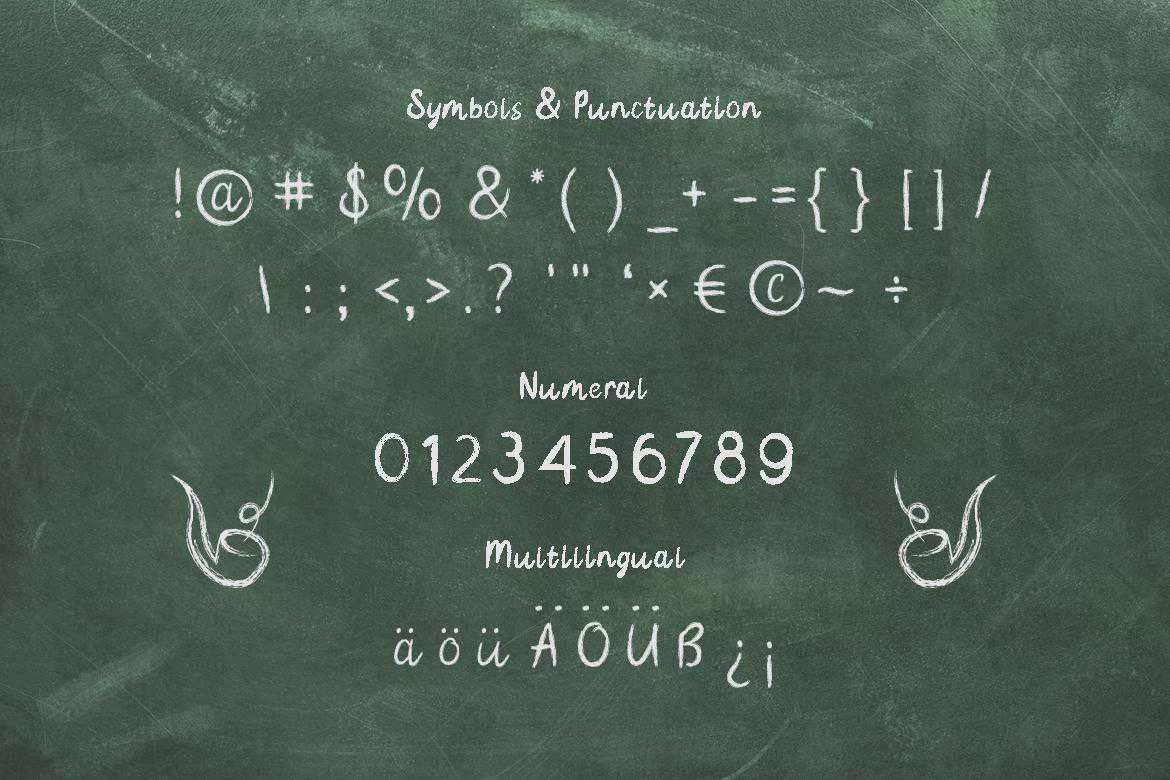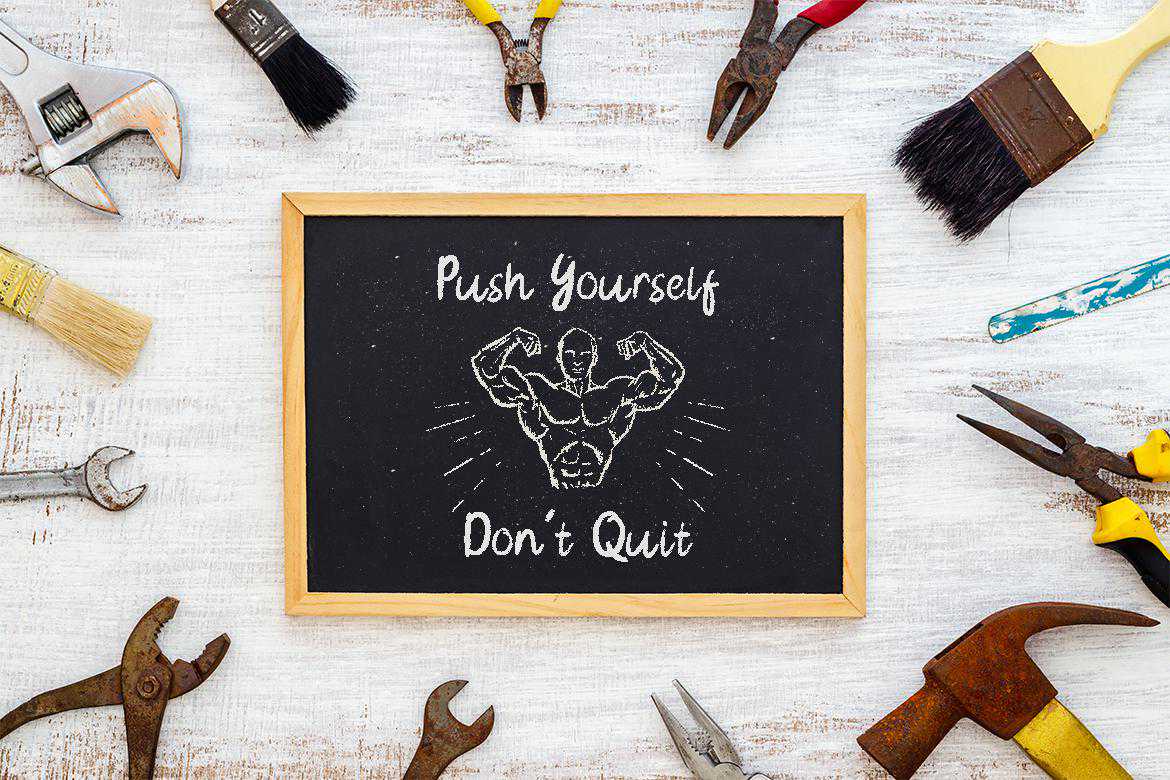
ScareMate是手工制作的DechalkFont。这款大胆、有趣、时尚的Font可用于各种不同的内容需求和项目。可制作GorgeousPartyVitations、打印报价、standoutpackaging或Beautiful衬衫!您甚至可以使用它来创建令人惊讶的标题、徽标、菜单和社交媒体。完整版本下载此处:ScaredMate是手工制作的。此粗体、有趣和时尚的字体可用于各种不同的内容需求和项目。创建GorgeousPartyVitations、打印的报价、standoutpackaging或美丽的衬衫!您甚至可以使用它来创建令人惊讶的标题、徽标、菜单和社交媒体。完整版本下载: